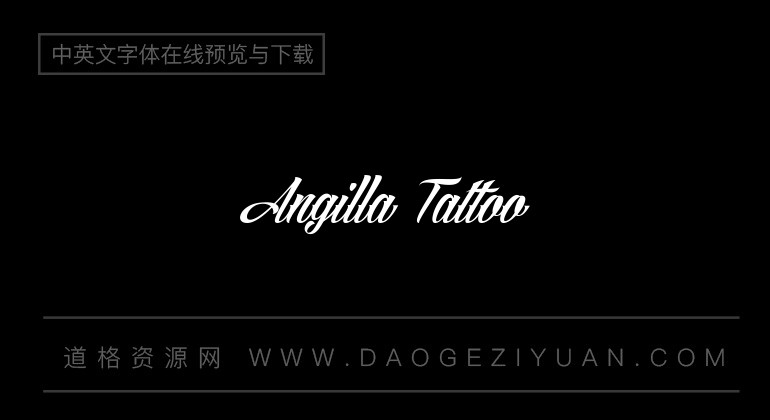
Angilla Tattoo
Angilla Tattoo是一种带有手写风格的装饰性字体,由巴西设计师 Marcelo Magalhães创作。它最初是为某个具体的纹身设计项目而创作的,后来被发展为一种可供广泛使用的字体。 Angilla Tattoo字体具有阴影和曲线等装饰元素,它的字母形状非常独特,结合了曲线和尖锐的角度,使它具有一种独特的视觉效果。该字体包含大写和小写字母、数字、标点符号和符号,可以用于创意设计、海报、书籍封面、品牌标识、纹身等多种用途。 总的来说,Angilla Tattoo字体是一种独特的手写风格字体,适用于需要引人注目、独特视觉效果的设计项目。
Angilla Tattoo是一款非常不错的手写艺术字体,具有很好的视觉感,适合于文化类的宣传设计、商业类品牌的广告和产品包装设计以及个性化文字排版等较多场景。